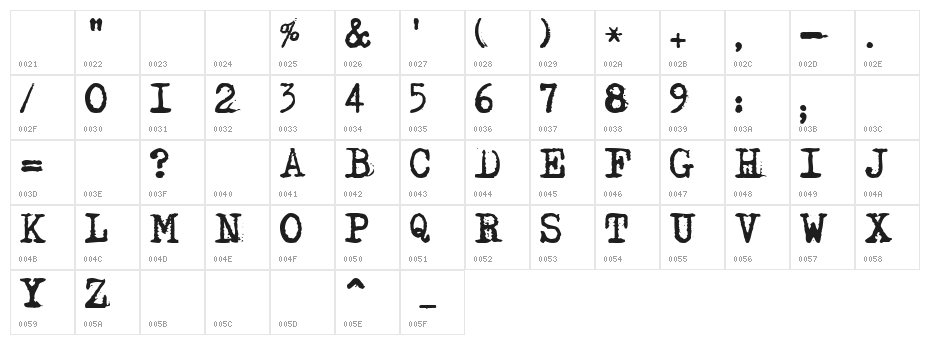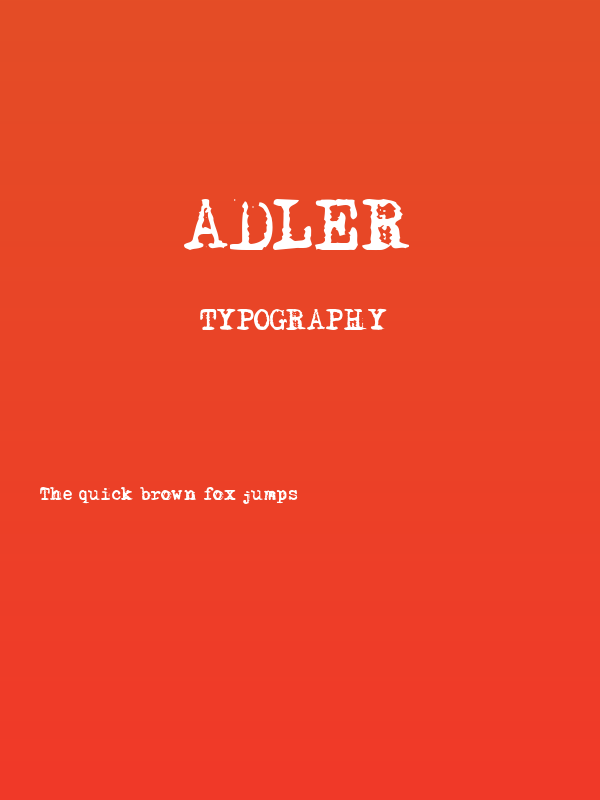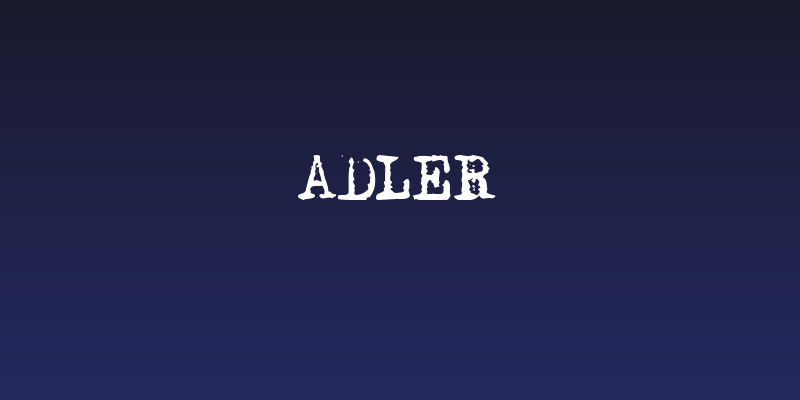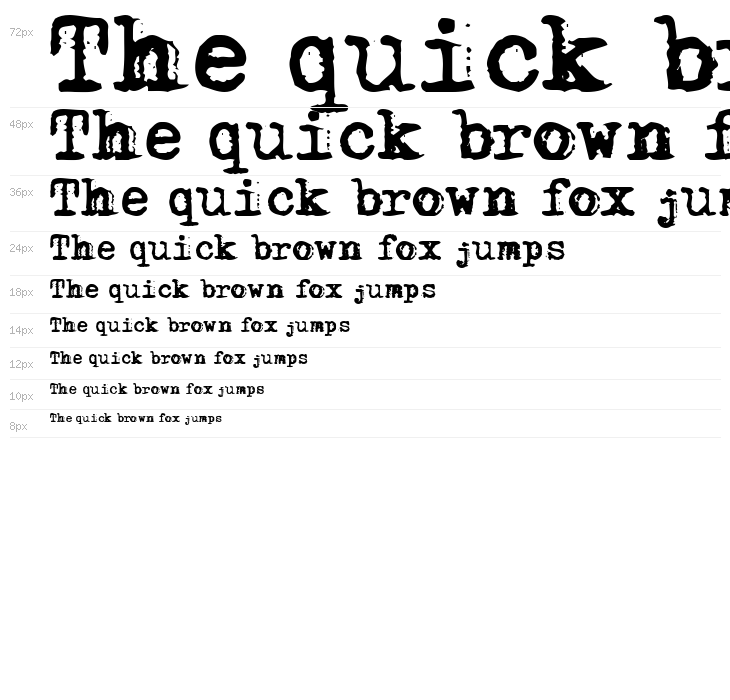
Adler Font
| Gesamtstil | Vintage |
| Vorgeschlagene Projekte | Ideal for vintage-themed posters, album covers, book titles, and branding that requires a bold, nostalgic touch. |